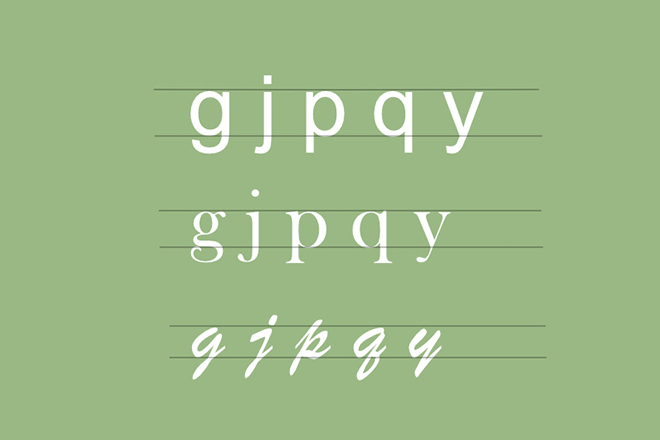
Was ist die Unterlänge in der Typographie?
Was ist ein Absteiger in der Typografie?
In der Welt der Typografie spielt jede Kurve, Linie und Strich eine entscheidende Rolle bei der Gestaltung von lesbarem und visuell ansprechendem Text. Zu diesen nuancierten Elementen gehören Unterlängen, die verlängerten Schleifen bestimmter Kleinbuchstaben, die unter die Grundlinie fallen.
In diesem schnellen Leitfaden erforschen wir Unterlängen, ihre Bedeutung im Design und den Einfluss, den sie auf Lesbarkeit, Ästhetik und Abstände in typografischen Werken haben. Ob du ein erfahrener Designer oder ein Typografie-Enthusiast bist, das Verständnis von Unterlängen kann deine Wertschätzung und Anwendung von Textdesign verbessern.
Was ist eine Unterlänge in der Typografie?
Was ist ein Absteiger?
Absteiger sind die Teile von Kleinbuchstaben, wie ‚g‘, ‚j‘, ‚p‘, ‚q‘ und ‚y‘, die unter die Grundlinie einer Schrift fallen.
Die Grundlinie ist die unsichtbare Linie, auf der die meisten Buchstaben sitzen, und Unterlängen fallen unter diese Linie und fügen dem Text Tiefe und Dimension hinzu. In einigen Schriftarten können die Buchstaben ‚f‘ und ‚z‘ ebenfalls subtile Unterlängenelemente aufweisen, obwohl dies je nach Schriftdesign variiert.
Die Rolle von Unterlängen in der Typografie
Die Rolle von Absteigern in der Typografie
Unterlängen spielen eine entscheidende Rolle bei der Lesbarkeit und dem Erscheinungsbild von Texten. Sie tragen zum vertikalen Rhythmus einer Textzeile bei, indem sie das visuelle Gewicht und die Verteilung des Weißraums ausbalancieren.
In Handschrift und Kalligrafie ermöglichen Unterlängen expressive Verzierungen, während sie in digitaler und gedruckter Typografie den Gesamtcharakter und den Fluss von Absätzen beeinflussen.
Einfluss auf Design und Lesbarkeit
Das Design von Unterlängen beeinflusst die Lesbarkeit von Texten, insbesondere in dichten Textblöcken oder kleineren Größen. Ein gut proportionierter Unterlängen kann die Klarheit des Textes verbessern, indem er ausreichende Trennung zwischen den Zeilen schafft und Buchstaben daran hindert, ineinander überzugehen.
Übermäßig lange oder dekorative Unterlängen können jedoch die Lesbarkeit stören, insbesondere in Kontexten, in denen der Platz begrenzt ist.
Unterlängen und Schriftgestaltung
Absteiger und Schriftgestaltung
Schriftgestalter gestalten Unterlängen akribisch, um den Stil, Ton und Zweck der Schrift widerzuspiegeln. Die Länge und Form der Unterlängen tragen zur Identität der Schrift bei, wobei Variationen von rein funktional bis hin zu elegant dekorativ reichen.
Es ist wichtig, ästhetische Anziehungskraft mit Praktikabilität auszubalancieren und sicherzustellen, dass die Unterlängen die beabsichtigte Anwendung der Schrift unterstützen, sei es für Fließtext, Überschriften oder künstlerische Kompositionen.
Die richtige Schriftart auswählen
Die Wahl der Schriftart beeinflusst maßgeblich die Effektivität der Unterlängen in einem bestimmten Designprojekt. Die Berücksichtigung der beabsichtigten Verwendung, der Zielgruppe und des Mediums der Schriftart ist entscheidend.
Zum Beispiel zeichnen sich Schriftarten, die für das Lesen von Texten über längere Zeit gedacht sind, oft durch zurückhaltendere Unterlängen aus, um die Lesbarkeit zu erhalten, während Display-Schriften möglicherweise ausgeprägtere und stilisierte Unterlängen für dekorative Effekte aufweisen.
Typografie mit Blick auf Unterlängen anpassen
Bei der Arbeit mit Typografie sind möglicherweise Anpassungen erforderlich, um die spezifischen Merkmale von Unterlängen zu berücksichtigen. Dazu gehören Anpassungen des Zeilenabstands (Leading), des Kernings und des Layouts, um sicherzustellen, dass der Text ausgewogen und lesbar bleibt.
Du könntest auch das Zusammenspiel zwischen Oberlängen (den Teilen von Buchstaben, die über die Grundlinie hinausragen) und Unterlängen in Betracht ziehen, um einen harmonischen vertikalen Rhythmus zu schaffen.
Best Practices für Typografie mit Abstiegen
Behalte diese Tipps im Kopf, um das Beste aus Unterlängen im Typografie-Design zu machen.
1. Stelle ausreichenden Zeilenabstand (Leading) sicher
Passe den Zeilenabstand an, um ein angenehmes Leseerlebnis zu schaffen, und ermögliche es Unterlängen und Oberlängen aus benachbarten Zeilen, ohne visuelle Störungen nebeneinander zu existieren. Dies verbessert nicht nur die Lesbarkeit, sondern trägt auch zu einem ästhetisch ansprechenderen Layout bei.
2. Berücksichtige Unterlängen im Layout-Design
Integriere den Platz, der für Unterlängen in deine Layout-Designs benötigt wird, insbesondere bei engem Platzangebot oder Rastersystemen. Diese Überlegung kann verhindern, dass der Text gedrängt aussieht, und die Integrität des visuellen Flusses deines Designs erhalten.
3. Kombiniere Schriftarten mit kompatiblen Unterlängen